Tutorial Tipografía: cómo elegir el tipo de letra adecuado
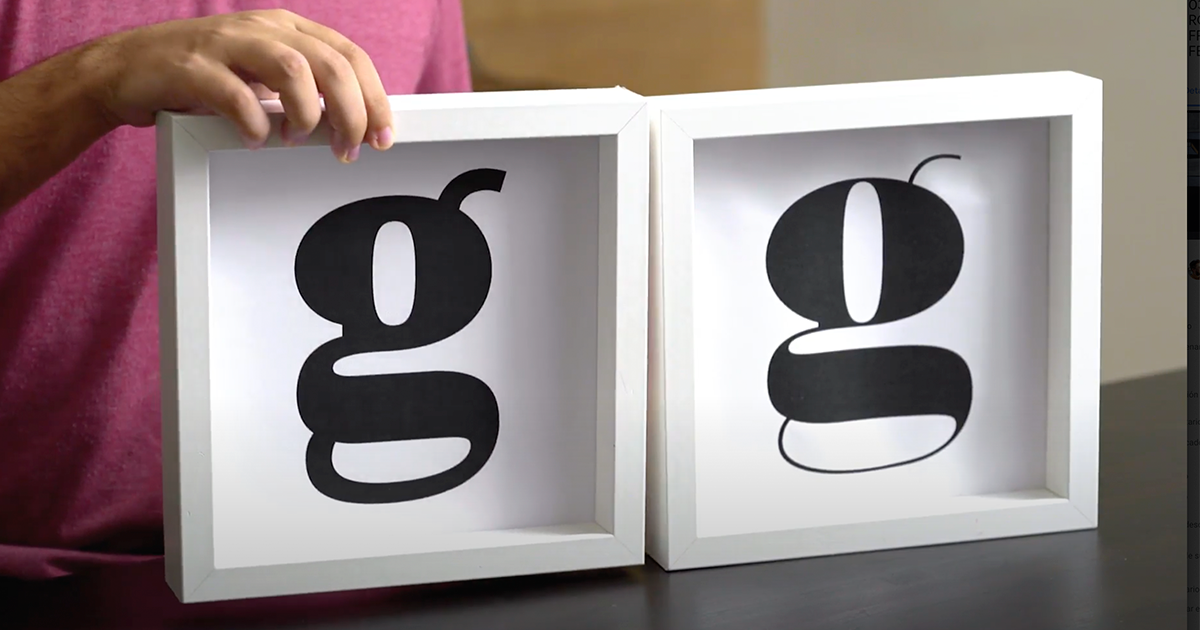
Descubre desde cero los mejores consejos para elegir una tipografía que consiga transmitir y potenciar tu mensaje de la mano de Álvaro Franca
La elección del tipo de letra adecuado para un proyecto es esencial para definir el tono de un diseño y sus características más importantes. Cada formato de fuente tiene diferentes propósitos y significados, lo que le permite transmitir y reforzar mensajes a través de un cartel, de un envoltorio, de un proyecto gráfico o de la portada de una revista, por ejemplo.
Para explorar todo el potencial de una tipografía, necesitas dominar el concepto de tamaños ópticos, o lo que es lo mismo, diseños adaptados de una misma letra para cumplir diferentes funciones. Algunas tipografías tienen estos tamaños y, aunque se basan en la misma familia, presentan diferencias cruciales cuando se utilizan, por ejemplo, en un cartel o en un texto.
En el siguiente vídeo, Álvaro Franca (@alvaroefe), diseñador gráfico y de tipografía, te ofrece consejos sobre cómo elegir el tamaño adecuado de una tipografía para potenciar tu proyecto. No te lo pierdas: